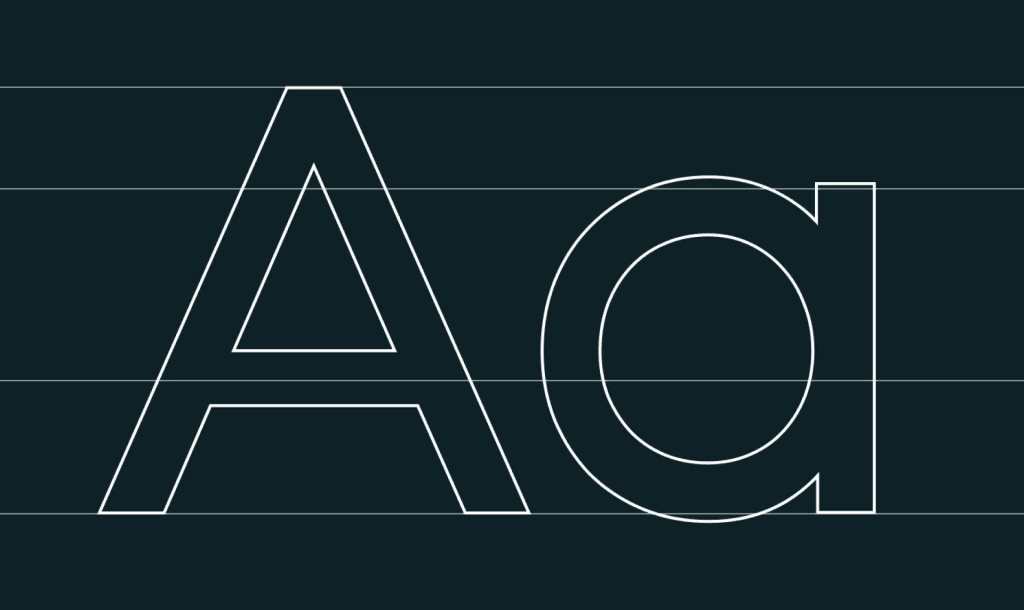
В России много компаний с богатой историей, крутыми клиентами и госзаказами, но при этом зачастую у них нет ни фирменного стиля, ни маркетинговой стратегии – а зачем? 50 лет же продавали и сейчас продадим!
К нам обратилась компания НИПИГАЗ, ведущий российский инжиниринговый центр. Полвека они управляют проектированием, поставками, логистикой и строительством, например, для Амурского ГПЗ «Газпрома» и «Арктик СПГ 2» НОВАТЭКа. И с этим все было прекрасно. Трудности возникали в другом месте – с оформлением коммуникационных площадок, визиток, благодарностей, презентаций. Компания постоянно платила за лицензию на шрифты – это для крупной бизнеса влетает в копеечку. Даже логотип оперативно не обновить.
Все это требовалось исправить.
Результаты
• Создали шрифты Nipigas Basic и Nipigas Extra, соответствующие фирменному стилю бренда.
• Сегодня клиент использует оба шрифта в логотипе, в маркетинговых материалах, на сайте и в социальных сетях.
Пример использования шрифтов Nipigas Basic и Nipigas Extra, разработанных «Текстеррой» Пример использования шрифтов Nipigas Basic и Nipigas Extra, разработанных «Текстеррой» Пример использования шрифтов Nipigas Basic и Nipigas Extra, разработанных «Текстеррой» Пример использования шрифтов Nipigas Basic и Nipigas Extra, разработанных «Текстеррой»
Пример использования шрифтов Nipigas Basic и Nipigas Extra, разработанных «Текстеррой»
• Создали новую версию логотипа с использованием адаптированного шрифта Nipigas Basic.
Логотип до и после замены шрифта
Символы оригинального шрифта в логотипе немного сжаты по горизонтали – это нужно, чтобы сделать логотип более компактным и схожим с оригиналом
Проблема
У НИПИГАЗа не было собственного шрифта. Из-за этого регулярно возникали трудности:
• доступные и бесплатные для коммерческого использования шрифты не передают ценности бренда и не ассоциируются с ним;
• лицензионные шрифты стоят слишком дорого и при этом все равно не избавляют от головной боли: их можно использовать не во всех маркетинговых целях;
• из-за использования «чужих» шрифтов обновление логотипа и других элементов брендинга усложнялось.
Новый шрифт понадобился компании, чтобы отстроиться от других игроков рынка, сократить расходы (регулярная покупка лицензии дороже разработки шрифта с нуля) и упростить создание маркетинговых материалов.
Задачи
Нам нужно было разработать два шрифта, учитывая следующие ожидания клиента:
• геометрический шрифт без засечек;
• визуальное сходство с семейством шрифтов, использованных компанией ранее;
• практичность, универсальность;
• подчеркнуть отличительные черты, выделяющие бренд среди прочих.
Также нужно было внедрить новый шрифт в логотип компании, не нарушая фирменный стиль бренда.
Ход работы
Разработка шрифта заняла четыре месяца. Хороший результат для такого трудоемкого проекта: мы провели исследование шрифтов и изучили бизнес клиента, разработали четыре концепции и создали два вида шрифта с кириллическим и латинским алфавитом.
Погружение в задачу
В первую очередь мы изучили бизнес клиента и конкурентов. На начальном этапе всегда важно понять, какой он – бренд, для которого создается шрифт. Еще мы узнали пожелания заказчика и свели все данные в техзадание.
Исследования
Мы выяснили, что клиент хочет получить рубленый шрифт без засечек и приступили к изучению других гротескных шрифтов. Из числа рубленых гарнитур выбрали восемь, максимально соответствующих ожиданиям клиента. На этапе согласования выделили двух фаворитов, на основе которых и решили создавать новые шрифты – AvantGarde и Metropolis.
Референсы шрифтов
Перед созданием шрифта собирали референсы – это помогает уточнить техзадание и убедиться, что мы разговариваем с клиентом на одном языке
Эти шрифты максимально соответствовали целям клиента, подходили для использования и в цифровой, и в офлайн-среде.
Референс и готовый шрифт
Готовый шрифт оказался близок к референсу, как и просил заказчик
Создание концепции
На первом этапе разработки гарнитуры мы сделали пять наборов скетчей – отрисовали все символы из слова «НИПИГАЗ».
Создание концепции
Эти скетчи использовали, чтобы создать цифровые символы и протестировать их. Мы предложили сотрудникам компании-заказчика и фокус–группам оценить наборы символов. Получили ценные комментарии и исключили наименее привлекательные наборы.